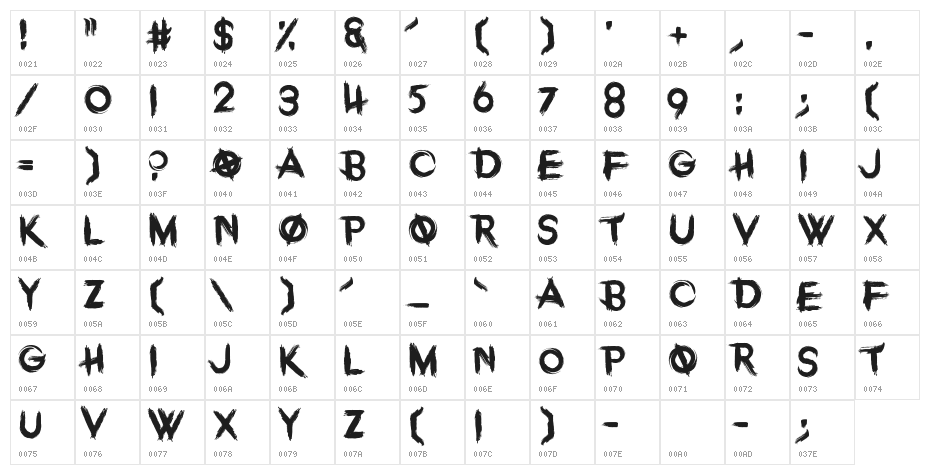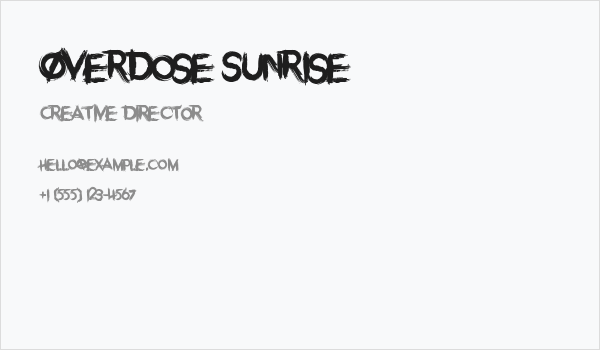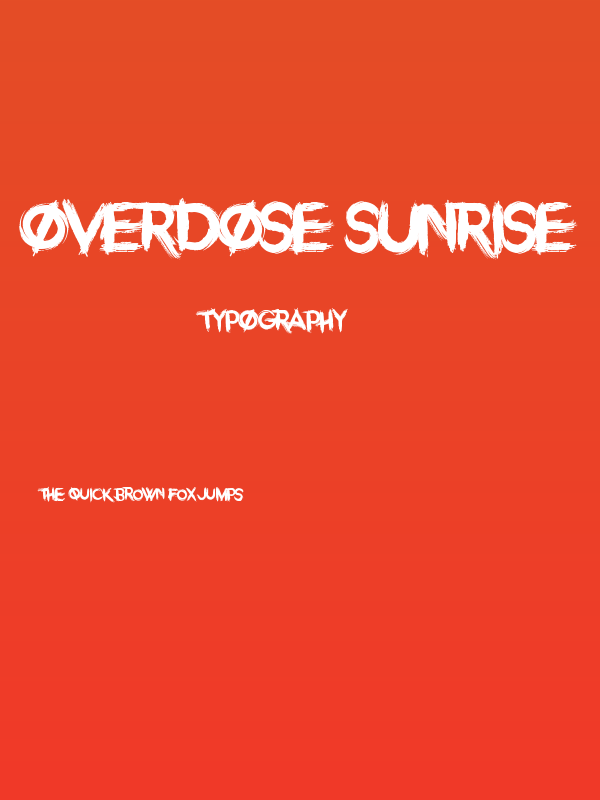
Overdose Sunrise Font
| النمط العام | Modern, Artistic |
| مشاريع مقترحة | Ideal for album covers, poster designs, street art-inspired branding, and creative advertising campaigns. |